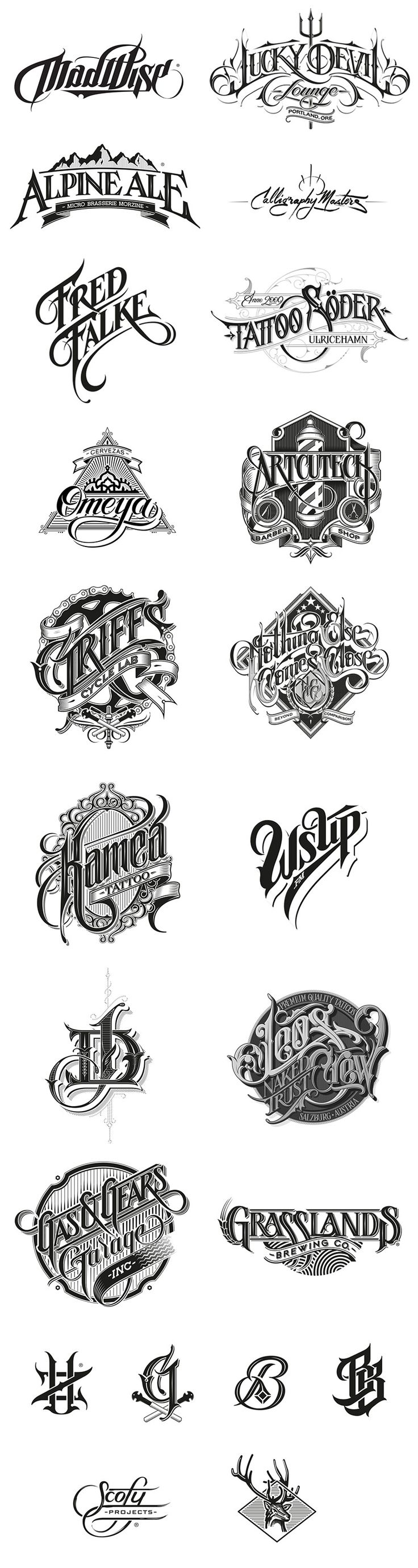
Ich suche diese Schrift (Biergun Brewery)
leider habe ich über die gängigen Seiten (whatthefont, etc.) nichts gefunden, daher meine Hoffnung hier:
kann mir jemand sagen, wie diese Font heißt?
Da wird man über die Font-Suchseiten auch nichts finden, denn das ist kein Font, sondern handgemachtes Lettering.
ein paar andere Beispiele für solche handgezeichneten Logos:
Was ja noch lange nicht bedeutet, dass er seine Lieblings-Schrift nicht auch immer wieder zeichnen kann, zumal der ja selber von "Handcrafted" schreibt.